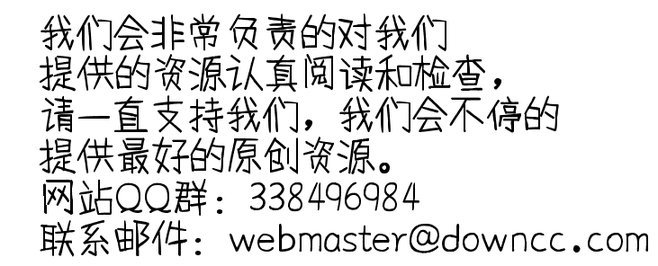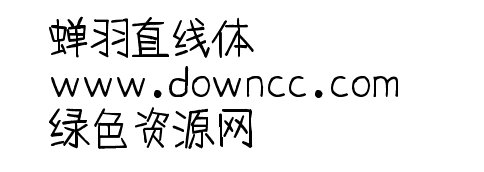
蟬羽直線體字體
蟬羽直線體字體兼具手寫字體和藝術(shù)字體的特色,給人清雅活潑的輕松體驗,字跡清晰線條明朗,字里行間盡顯飄逸之風(fēng),如果你喜歡,就來綠色資源網(wǎng)下載試試吧!
蟬羽直線體介紹
“蟬羽直線體13”是由王建剛獨立創(chuàng)作的一款符合GB2313-80標(biāo)準(zhǔn)的中文簡體字庫,可用于廣告設(shè)計、影視視頻制作、印刷、媒體顯示等領(lǐng)域。